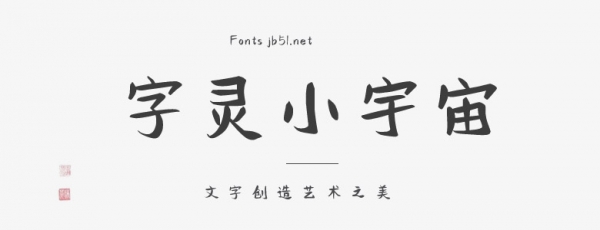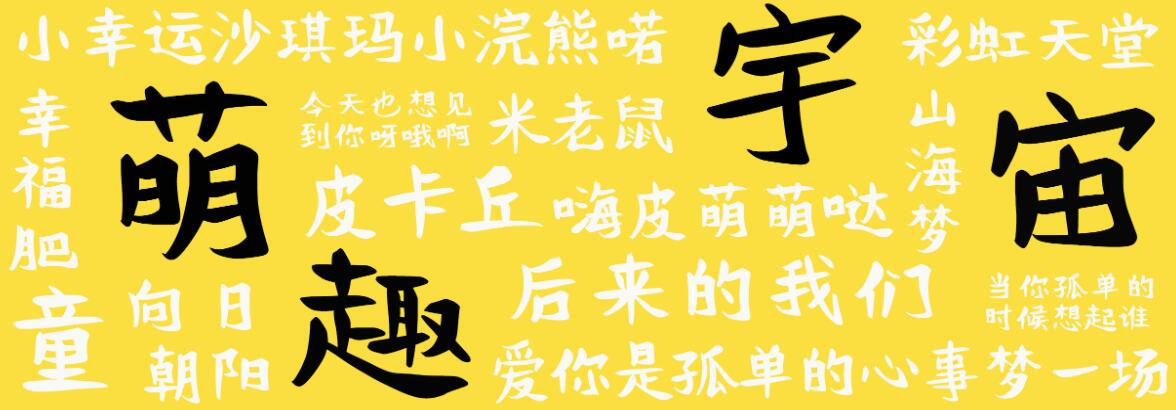
字靈小宇宙是一款手寫創(chuàng)意字體。字體結(jié)構(gòu)穩(wěn)健,筆畫舒展,字形輪廓不拘于一格,圓潤(rùn)修長(zhǎng)。字體結(jié)構(gòu)靈活,筆畫線條的粗細(xì)對(duì)比明顯,粗細(xì)交錯(cuò),起筆收筆為傾斜狀態(tài),字的風(fēng)格有趣而富有個(gè)性。
字靈小宇宙這款字體完美的展示了字形結(jié)構(gòu)中粗中有細(xì)、細(xì)中帶粗的變化之美,線條轉(zhuǎn)筆的弧度自然流暢,豎鉤、豎折的銜接處光滑、圓潤(rùn),字體顯得流暢自然。
這款字靈小宇宙體巧妙的簡(jiǎn)化了部分筆畫的書寫形態(tài),字體看上去簡(jiǎn)潔鮮明,筆畫之間粗細(xì)交錯(cuò),富有活力,令人印象深刻。字體風(fēng)格舒展柔和,適用于平面設(shè)計(jì)、廣告設(shè)計(jì)以及排版印刷等行業(yè)。